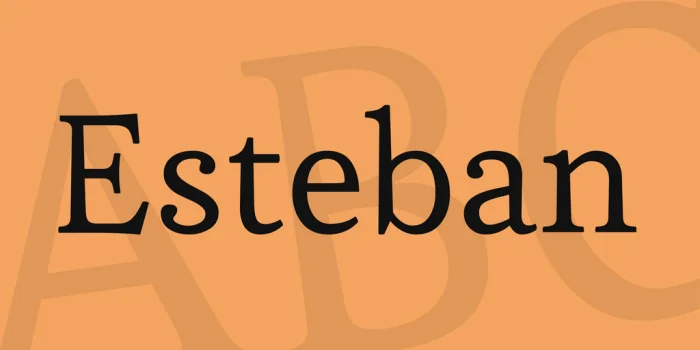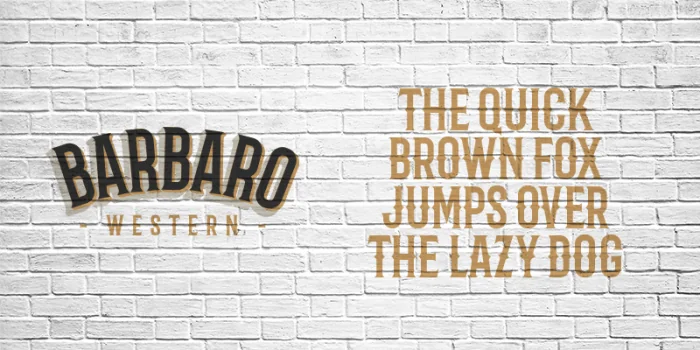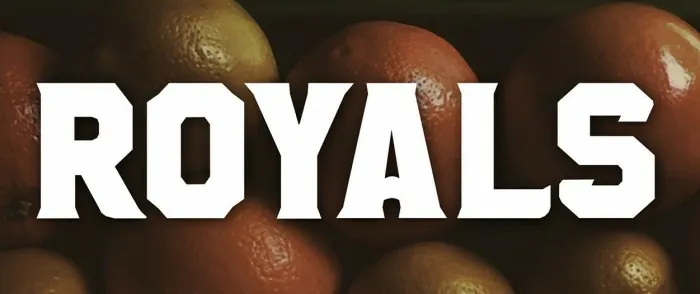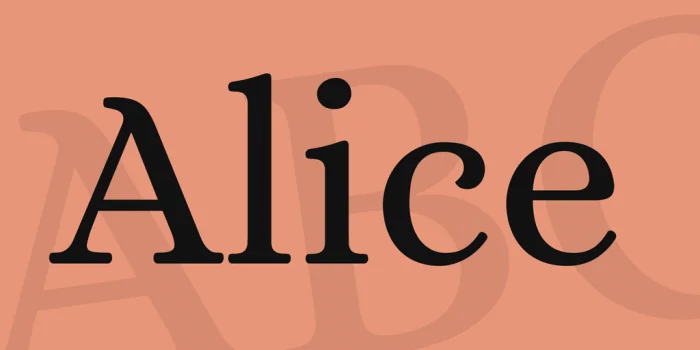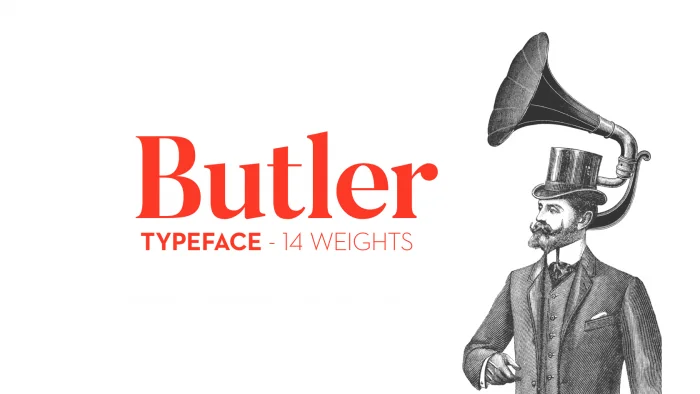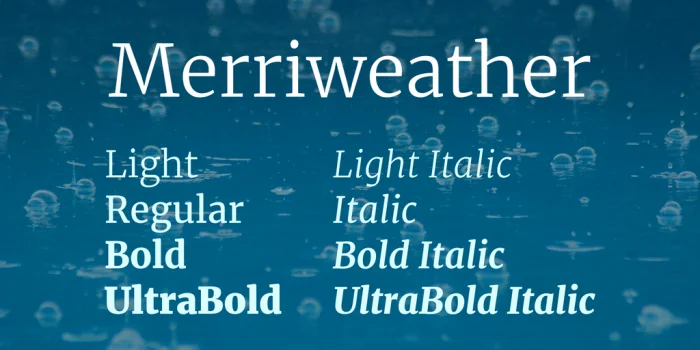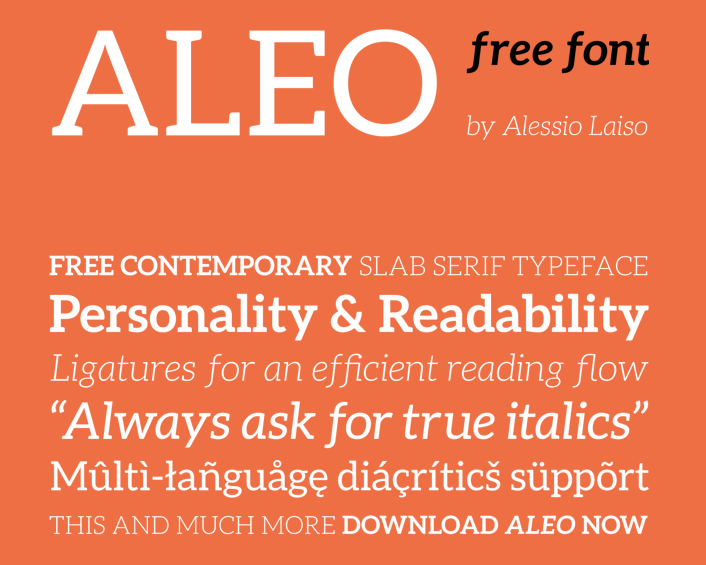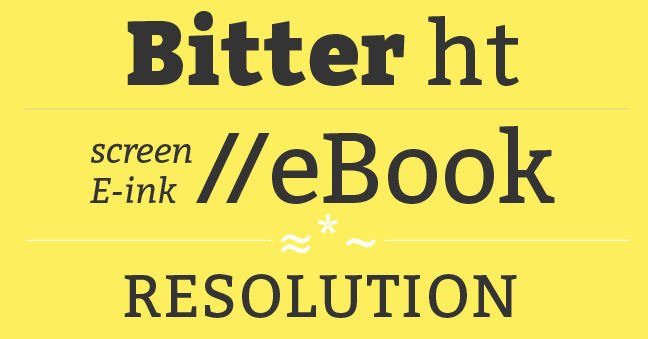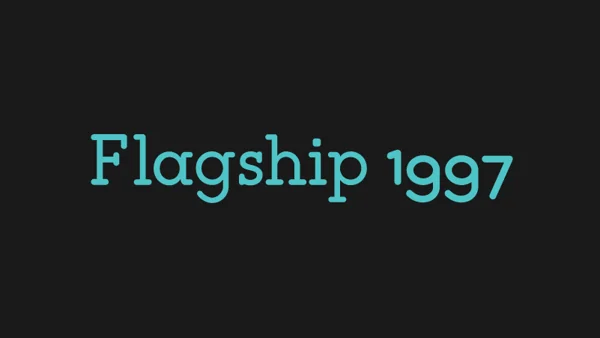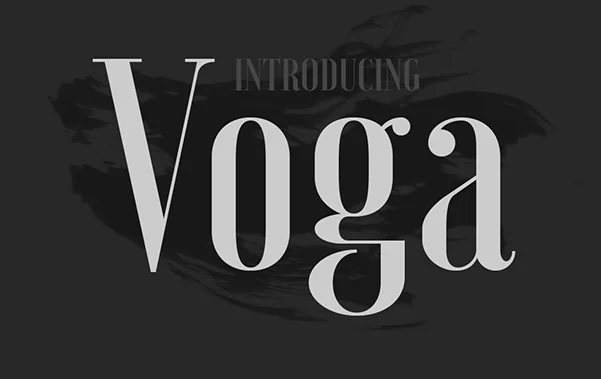
Las fuentes serif son las más utilizadas en el texto que solemos leer en libros, documentos… ¿Quién no conoce la Georgia, la Garamont, la Courier New? Estas tipografías son algunas de las incluidas dentro de serif.
¿Cómo son las fuentes serif?
Son tipografías de palo pero con la característica añadido de las viejas fuentes, con esa terminación para darle estilo antiguo.
Aleo
Es una fuente que la tienes además en cursiva.
Flagship
Esta tipografía la tienes en formato regular y negrita.
Voga
Fuente ideal para que utilices en títulos.
Musket
Brela
Es una fuente regular que se lee bien.
Akura Popo
Fenix STD
Es una tipografía muy elegante y que es ideal para utilizar en la lectura de textos.
Hagin Serif
Esta tipografía la podrás utilizar para cualquier trabajo de diseño gráfico, web, camisetas, logos, posters,…
Bitter ht
La tienes disponible en estilo normal, cursiva, negrita y negrita cursiva.
Esteban
Espacio Novo
Tipografía simple y limpia.
Tipografía Barbaro
Fuente Royal
Esta tipografía está en 4 variantes: regular, regular italic, rush y rush italic.
Fuente Alice
Butler
Merriweather fuente
Arctic
Tipografía con acentos y con la ñ. Queda muy bien para títulos.